1、Holland Script
这是一款比较细的硬笔手写体,字形美丽优雅。非常适合摄影,签名,品牌推广。
2、Oraqle Script
种来自Union Hands的笔刷字体,具有醒目的笔触和真实的笔刷纹理,外观整洁。可用用于徽标,印刷品,徽章,包装,标题,海报,T恤/服装,贺卡和婚礼请柬等。
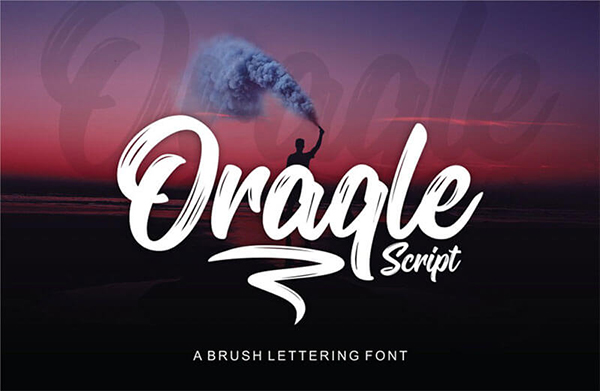
3、Bahagia
Bahagia是一种华丽的签名字体,为字体设计带来了无穷无尽的美感,在每个字母和笔画中都充满了长达数世纪的魅力和全部力量。常用于徽标,邀请,卡片,包装,并支持多种多语言。
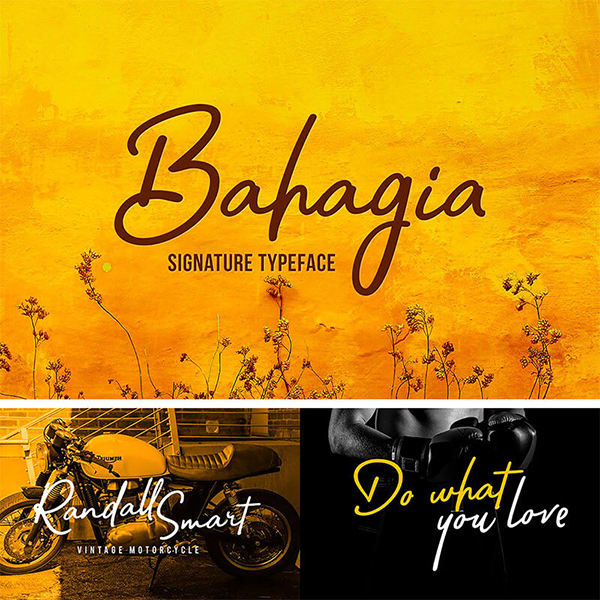
4、Viana
Viana Script是一种优雅的手写字体,常用于博客,徽标,手工制作,婚礼邀请,报价。
5、Ameliea
6、Signatura Monoline
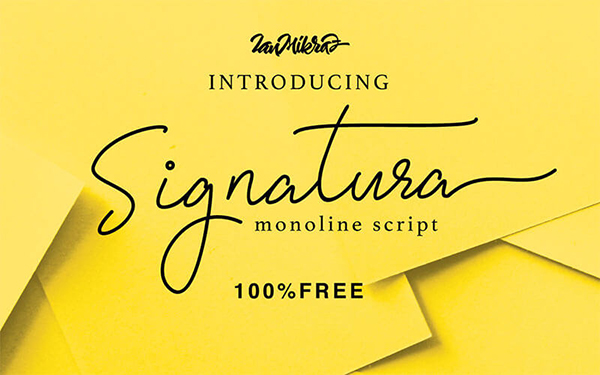
7、Oh Wonder
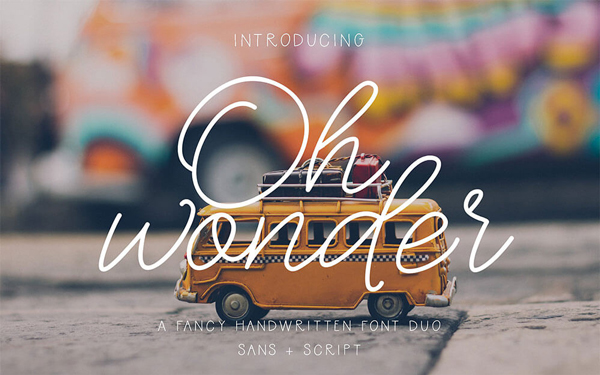
8、Aamonoline
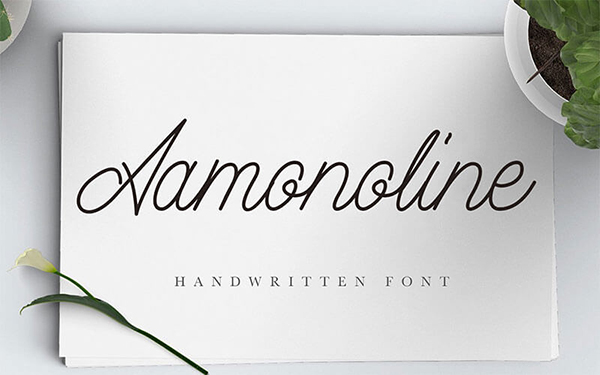
9、Lisbon Script
10、MademoiselleNS
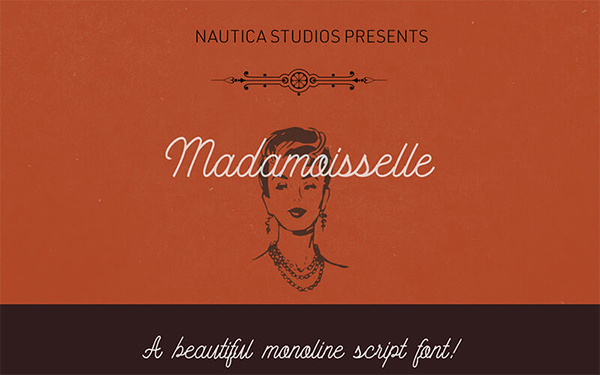
11、Wilderness Typeface Regular
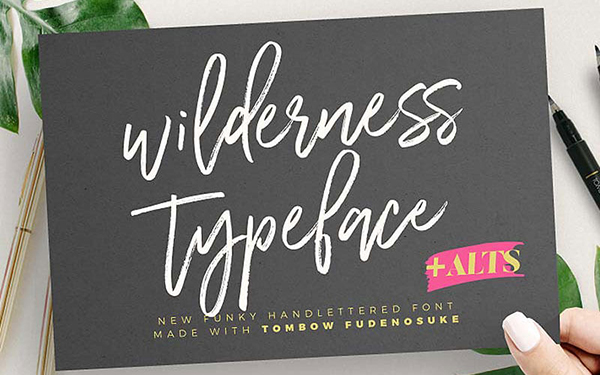
12、Quentin
字体使用干燥的笔触书写而成,自然流畅并有自己的个人品味。 Quentin将成为品牌推广的完美之选,因为它具有标志性的触感,也非常适合产品包装和流行的社交媒体广告。
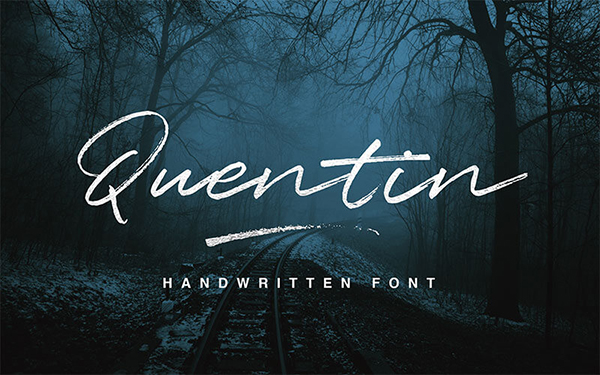
13、Tormentor
保留手写的纹理,并以草书的形式书写完成。
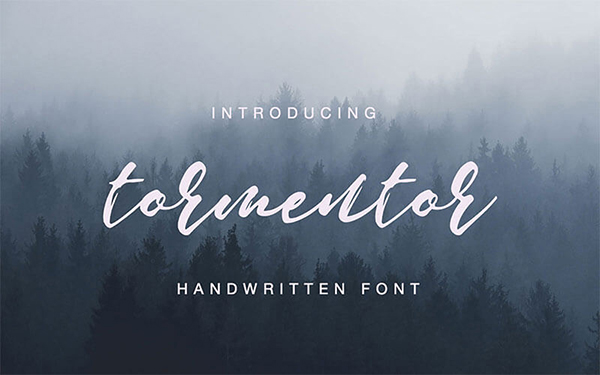
14、Antro Vectra
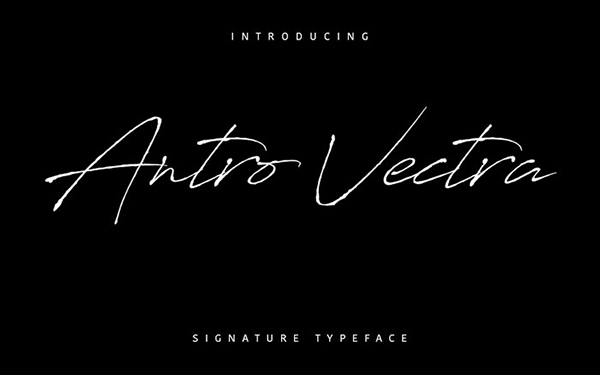
15、Andara Script
16、Santana Script
17、Larquette Typeface
18、Connoisseurs Typeface
是一款优雅的手写笔刷字体,充满了时尚,艺术感。
19、Salted Mocha Regular
20、Brownhill Script
21、Jullian
22、Foundry
23、Hallelujah
24、Cursive Script